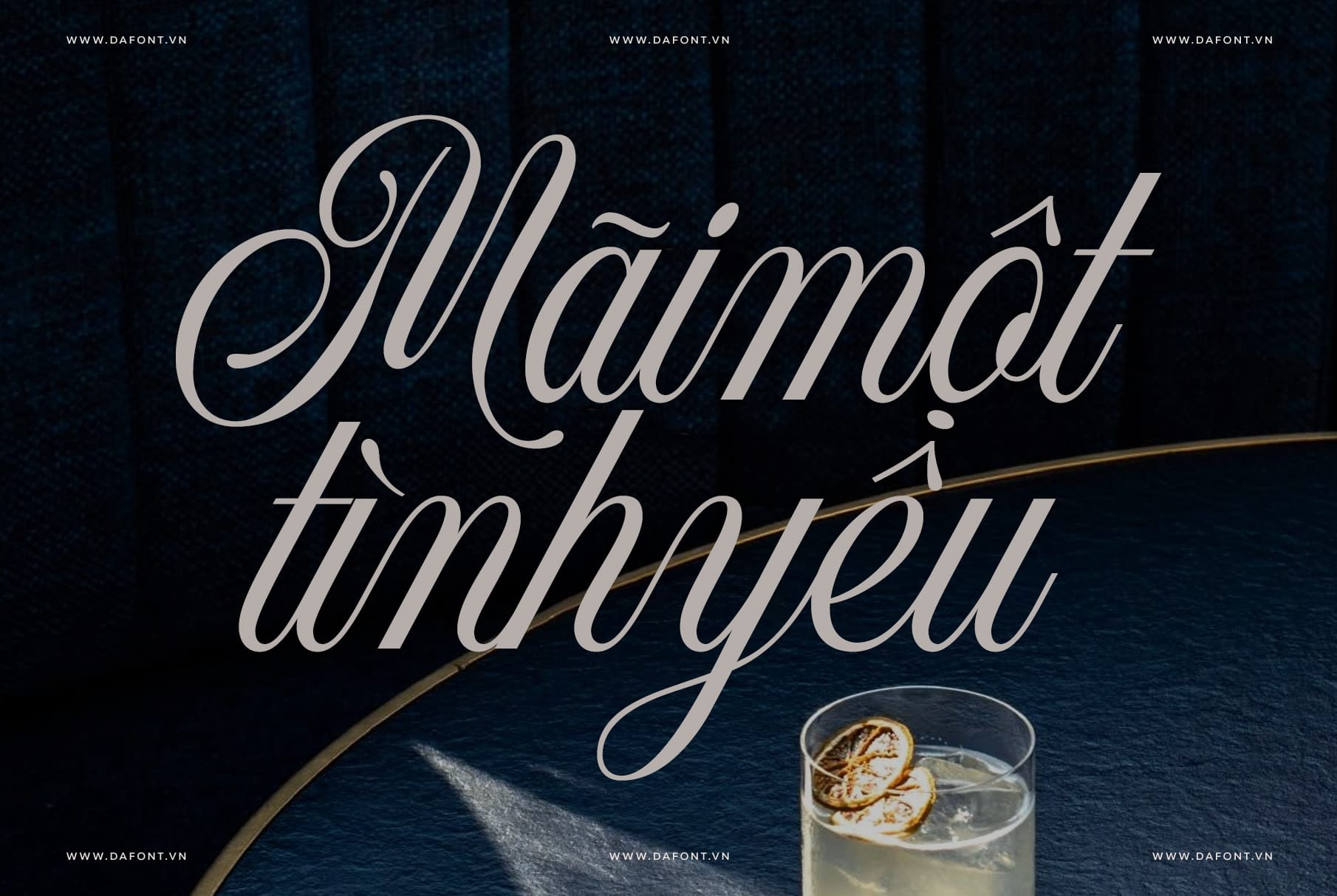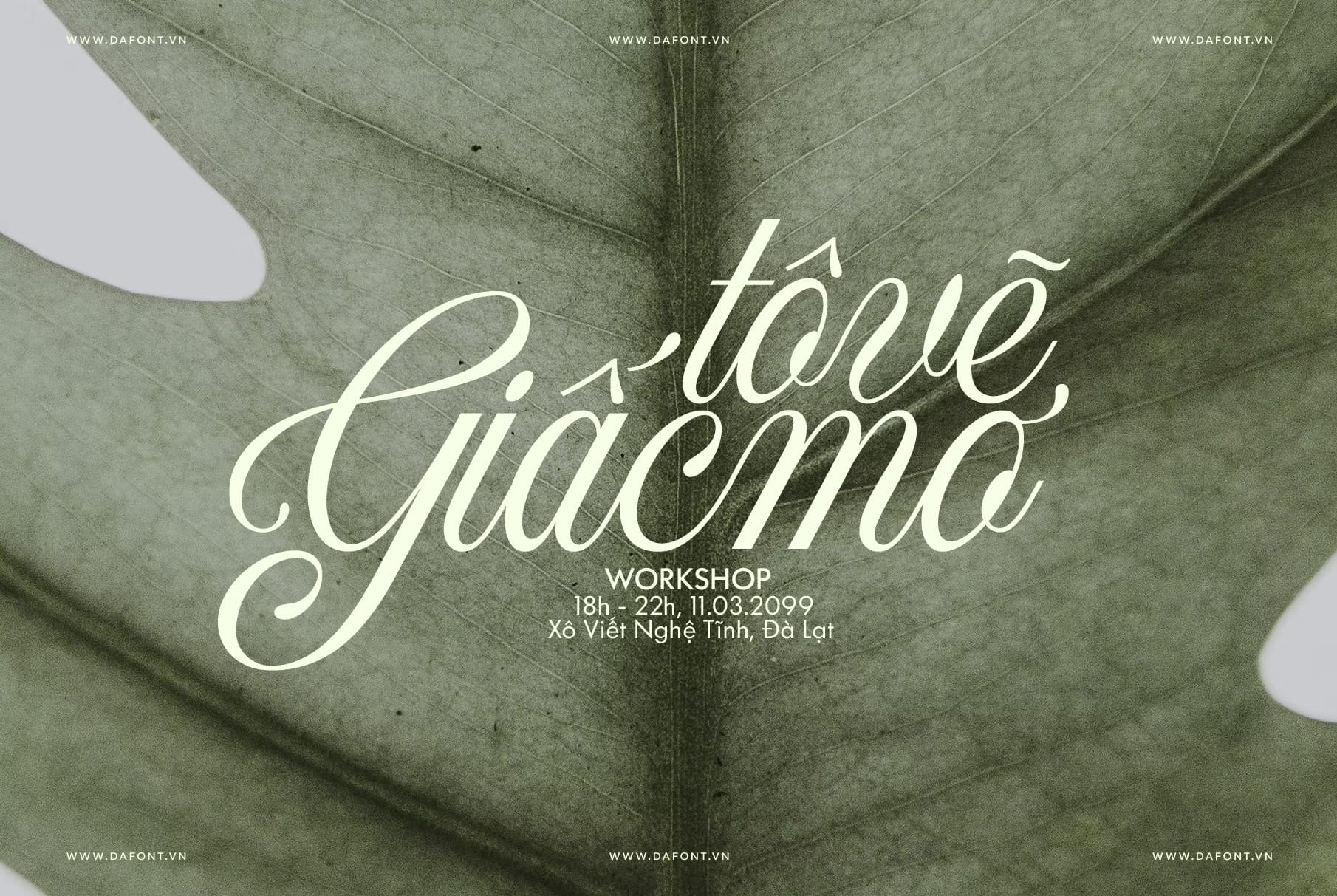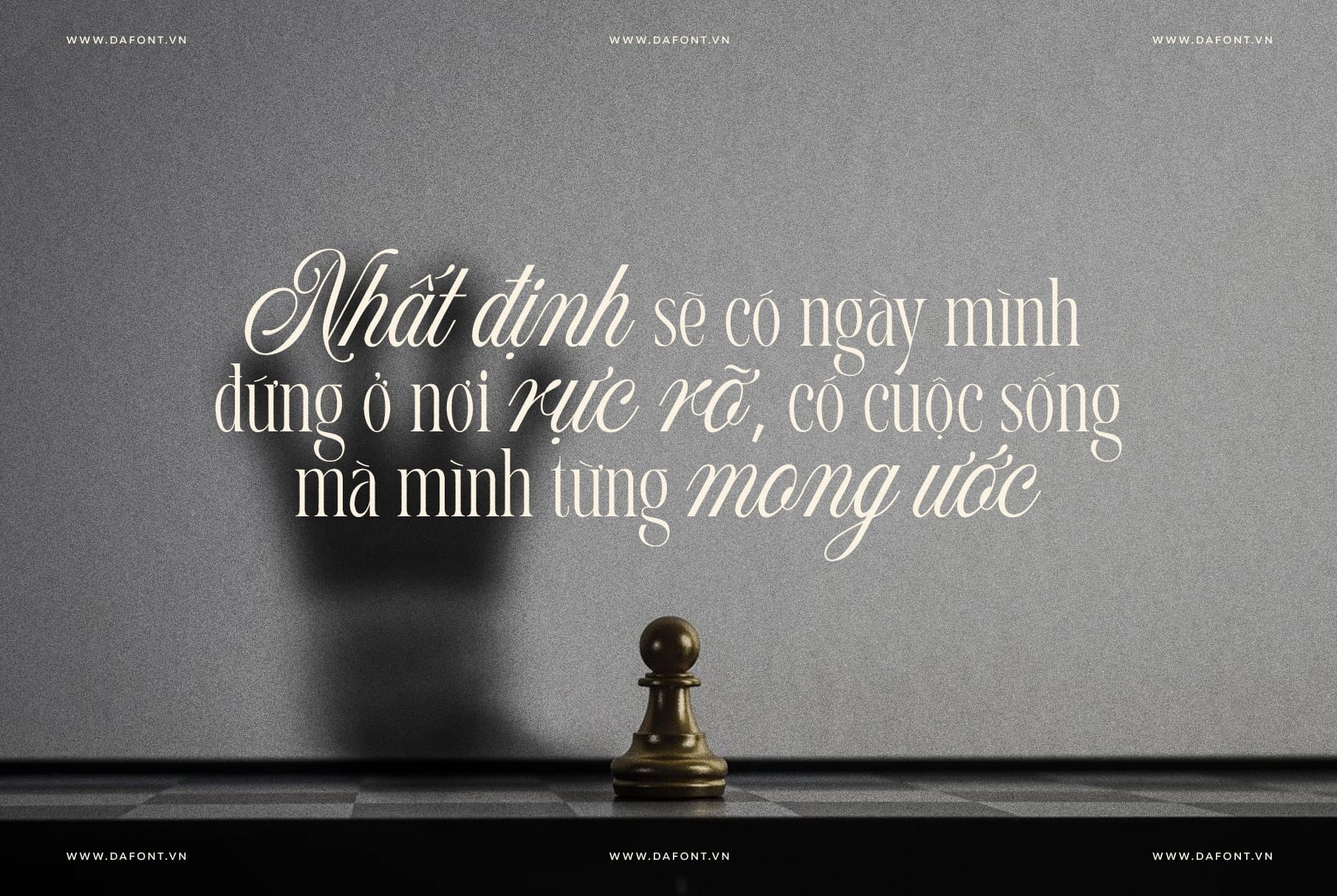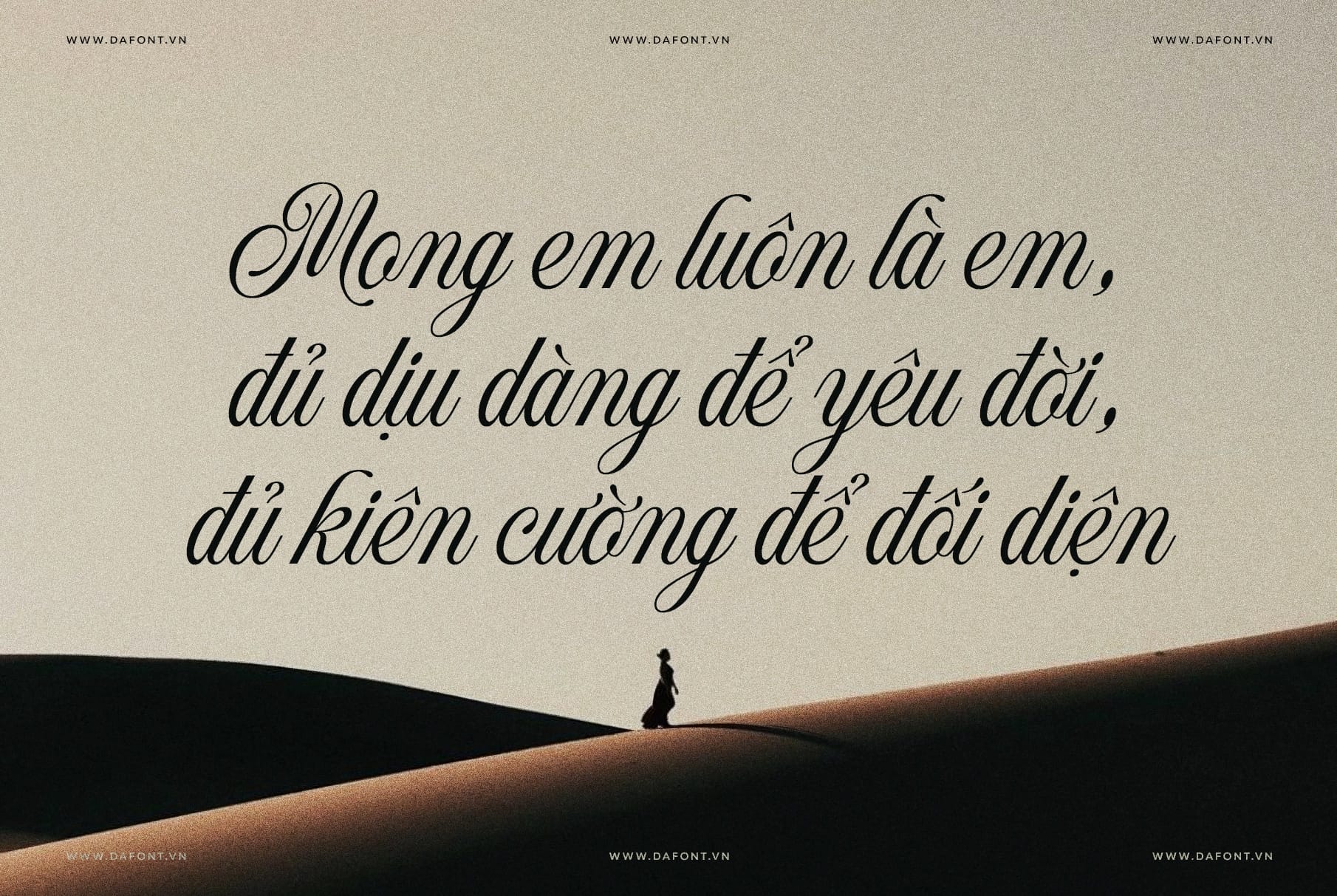
DFVN TAN – ALASTAIRE là một kiểu chữ display script mang vẻ đẹp lãng mạn và sang trọng, lấy cảm hứng từ thời kỳ Romantic. Font sở hữu các đường nét mềm mại, giàu tính trang trí, tạo cảm giác tinh tế và bay bổng ngay từ cái nhìn đầu tiên.
TAN – ALASTAIRE được thiết kế như một script cao cấp, có thể đứng độc lập hoặc kết hợp với các typeface khác. Nhờ khả năng pairing linh hoạt, font này nhanh chóng được ưa chuộng trong các dự án branding, thiệp cưới, thiệp mời, thời trang và ấn phẩm cao cấp.
Đặc điểm nổi bật của DFVN TAN – ALASTAIRE
Điểm mạnh của TAN – ALASTAIRE nằm ở form chữ mềm mại, nữ tính nhưng vẫn giữ được sự sang trọng, chín chắn. Kết cấu chữ được chăm chút kỹ, độ tương phản nét vừa phải giúp font vừa trang trí, vừa không quá khó đọc ở kích thước lớn.
Một số đặc trưng nổi bật:
- Phong cách display script lấy cảm hứng từ thời kỳ lãng mạn, phù hợp các thiết kế mang tính cảm xúc.
- Đường nét uyển chuyển, nhiều chi tiết lượn cong, tạo cảm giác viết tay cao cấp chứ không phải script phổ thông.
- Font đủ “đậm chất riêng” để đứng một mình, nhưng cũng được tối ưu để kết hợp với serif hoặc sans serif trong cùng layout.
- Thiết kế hướng tới các ứng dụng hiển thị (display): tiêu đề, logo, tên thương hiệu, chữ trang trí trên bìa, thiệp cưới…
Nhờ những đặc điểm này, TAN – ALASTAIRE không phù hợp dùng cho đoạn text dài mà lý tưởng cho những vị trí cần nhấn mạnh và tạo ấn tượng đầu tiên.
DFVN TAN – ALASTAIRE phù hợp trong những thiết kế nào?
Sự sang trọng của TAN – ALASTAIRE biến nó thành một “trợ thủ” đắc lực cho các hạng mục thiết kế đòi hỏi tính thẩm mỹ cao cấp:
- Thiết kế thiệp cưới & Sự kiện: Hoàn hảo để làm điểm nhấn cho tên cô dâu chú rể hoặc các tiêu đề trên thiệp mời, menu tiệc.
- Nhận diện thương hiệu (Branding): Rất phù hợp cho các logo thuộc lĩnh vực làm đẹp, mỹ phẩm, thời trang cao cấp hoặc trang sức.
- Thiết kế bao bì (Packaging) & Editorial: Tạo sự thu hút trên bìa sách, tạp chí thời trang hoặc nhãn mác sản phẩm mang phong cách thanh lịch.
TIP nhỏ cho bạn: DFVN TAN – ALASTAIRE đứng một mình đã đủ tỏa sáng, nhưng nó còn kết hợp cực kỳ ăn ý với các font chữ khác. Hãy thử “pair” nó với một font Serif cổ điển hoặc một font Sans-serif mỏng, hiện đại. Sự tương phản giữa nét chữ bay bổng của Alastaire và sự cứng cáp của các font tĩnh sẽ giúp layout của bạn trở nên chuyên nghiệp và có chiều sâu hơn.
Kết luận
Tóm lại, DFVN TAN – ALASTAIRE là một kiểu chữ mang vẻ đẹp lãng mạn, sang trọng và đầy cuốn hút, rất phù hợp với những thiết kế cần sự mềm mại và dấu ấn thẩm mỹ riêng. Với phiên bản Việt hóa được tối ưu dấu chỉn chu, font càng trở nên dễ ứng dụng hơn trong các thiết kế tiếng Việt như logo, poster, bìa sách, thiệp cưới hay social post. Nếu bạn đang tìm một font script vừa tinh tế vừa nổi bật, TAN – ALASTAIRE chắc chắn là lựa chọn rất đáng để trải nghiệm.